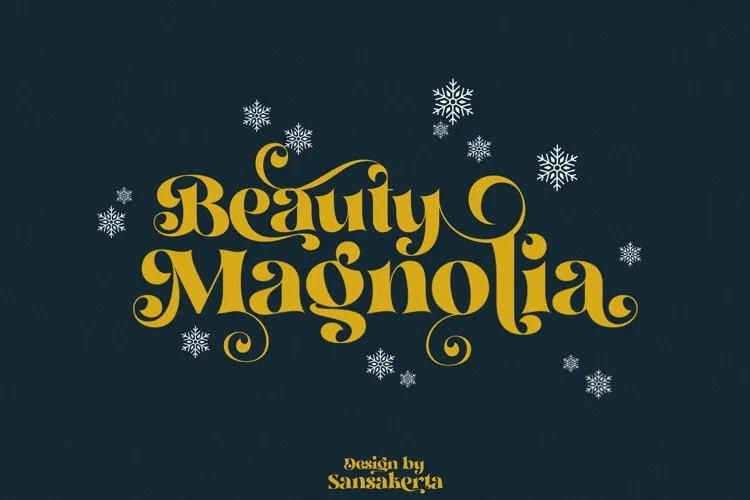
Beauty Magnolia Serif Font – Download Grátis
A Beauty Magnolia Serif Font é uma tipografia elegante com um toque nostálgico perfeito para aplicativos que valorizam sofisticação moderna e personalidade discreta. Desenvolvida e compartilhada pela equipe de designers da Sansakerta, esta fonte serif possui 30+ ligaturas e 97+ alternativas que permitem criar formas curvas e shapes belos em poucos segundos. Essas características tornam a Beauty Magnolia Serif Font uma escolha ideal para aplicativos como logotipos, masthead e frases de destaque. Suave, versátil e com um toque de brincadeira, esta fonte serif se combina perfeitamente com tipografias sans-serif ou script leve. Ela será uma ótima adição a qualquer projeto que deseja trazer elegância ao texto, sem perder a sensação nostálgica que tanto pode ser valorizada em tempos atuais.